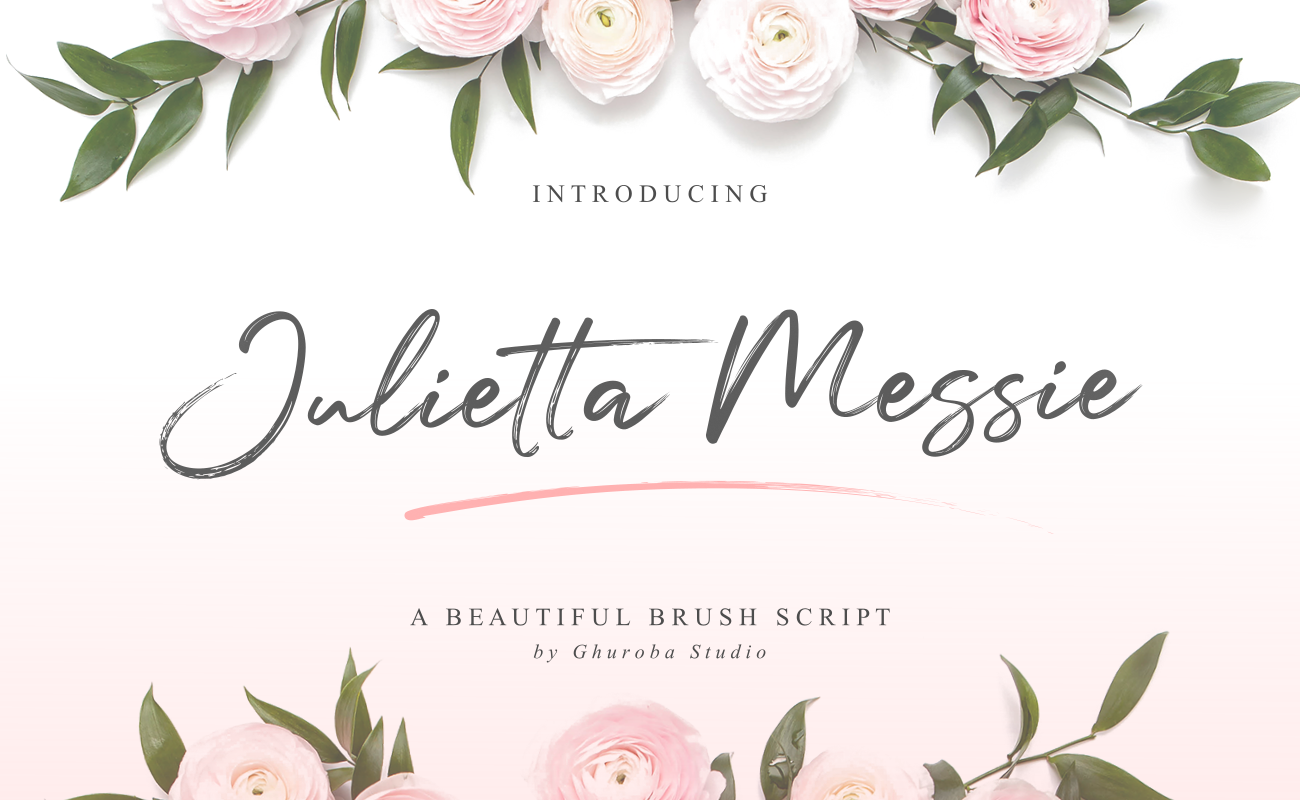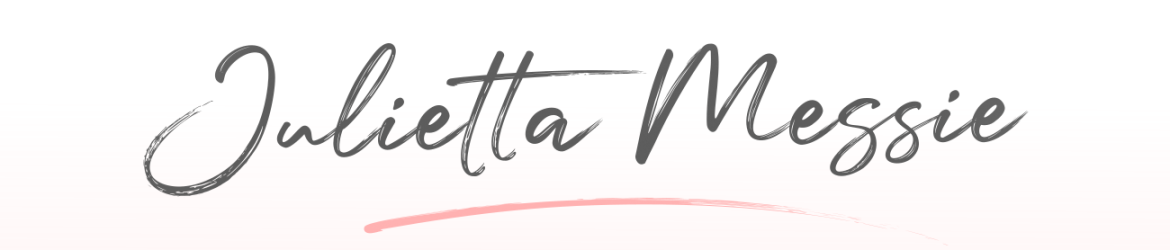
Julietta Messie Brush Script Font – Download Grátis
A Julietta Messie Brush Font é uma elegante seleção para aqueles que desejam adicionar um toque sofisticado a seus projetos de design. Suas linhas delicadas e curvas suaves fazem dela uma escolha perfeita para quem quer incorporar um ar refinado em sua próxima criação. Ela é ideal para designers que buscam trazer um brilho a seus trabalhos, adicionando um toque luxuoso e sofisticado ao design. Com seu traçado delicado e fluido, essa fonte não apenas se destaca por sua beleza visual, mas também pela capacidade de tornar qualquer projeto mais envolvente e memorável. Ideal tanto para criar cartazes atraentes quanto para adicionar um toque elegante em editoriais de design gráfico, a Julietta Messie Brush Font é uma fonte que merece ser explorada por designers comprometidos com o resultado final do seu trabalho.
Designer: Ghuroba Studio